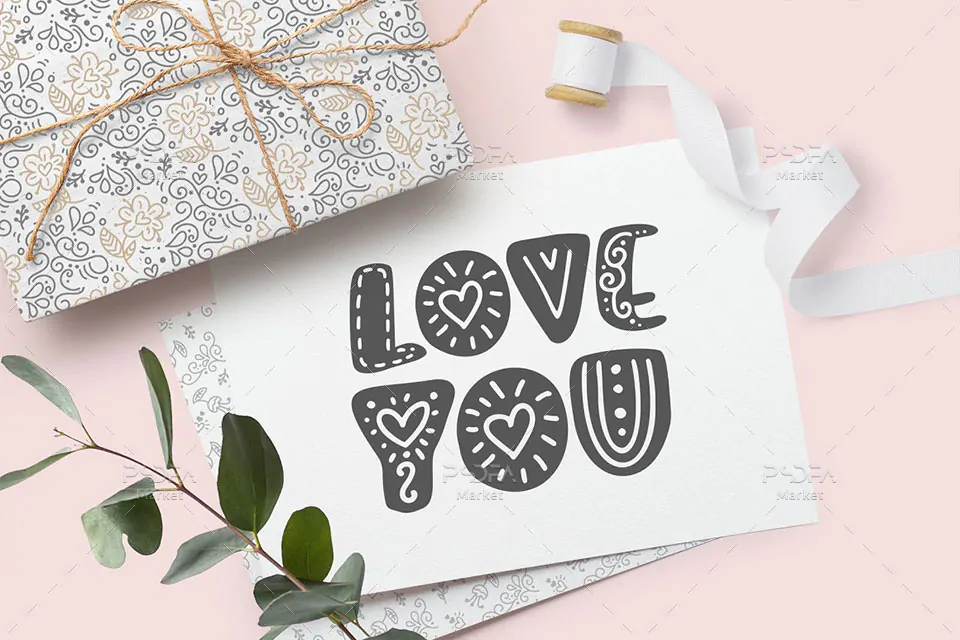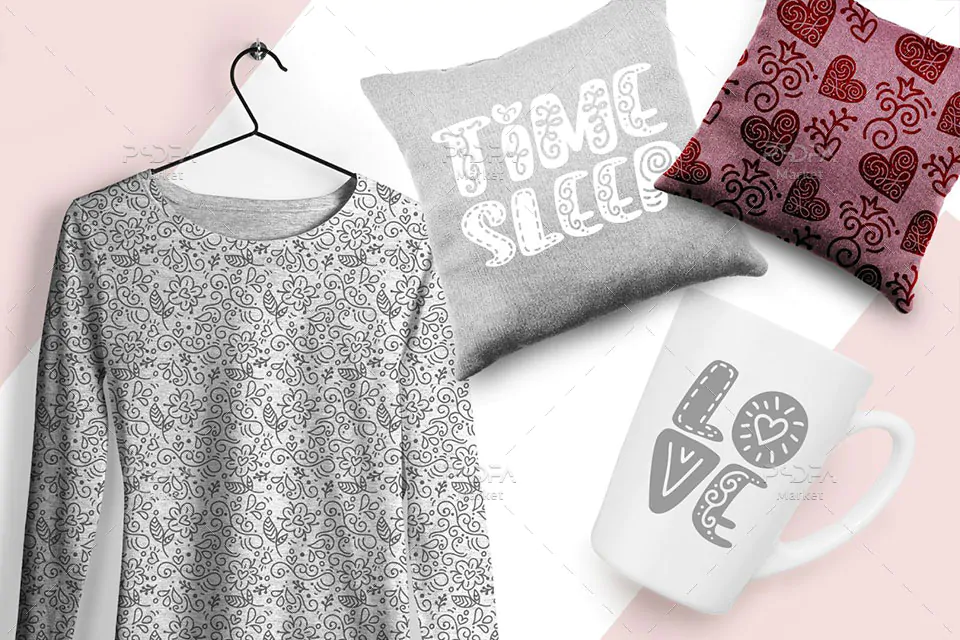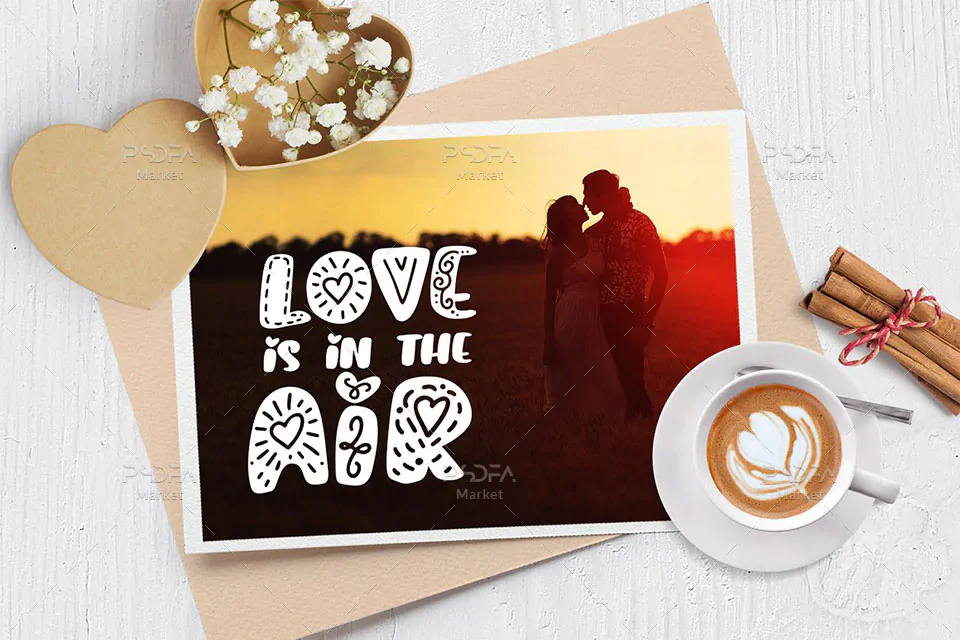
فونت تزئینی و دکوراتیو Soft Vintage مجموعهای فوق العاده زیبا از یک قلم انگلیسی فانتزی به همراه 6 پترن بدون درز تزئینی که مناسب جهت استفاده در طرح و پروژههای گرافیکی مختلف میباشند. این مجموعه پترن و فونت Soft Vintage در قالب فایلهای svg, otf, ttf, eps, png در فایل محصول قرار دارند که با نصب فایلهای otf در پوشه فونتهای سیستم میتوانید از این فونت زیبا در تمام نرم افزارهای گرافیکی و ویرایشگر متن استفاده کنید.
فونت فانتزی و کودکانه Yeti در وزن معمولی (Regular) و در دو سبک مختلف طراحی شده است که میتوانید از آن و این مجموعه طرح وکتور پترن در طراحی انواع کارت تبریک، کارت پستال، لوازم التحریر، ظروف یکبار مصرف، بسته بندی محصولات، تقویم، پوستر، قاب و کاور موبایل، بگهای خرید و هدیه، قاب عکس و صدها ایده دیگر استفاده کنید.
- وزن فونت: معمولی (Regular)